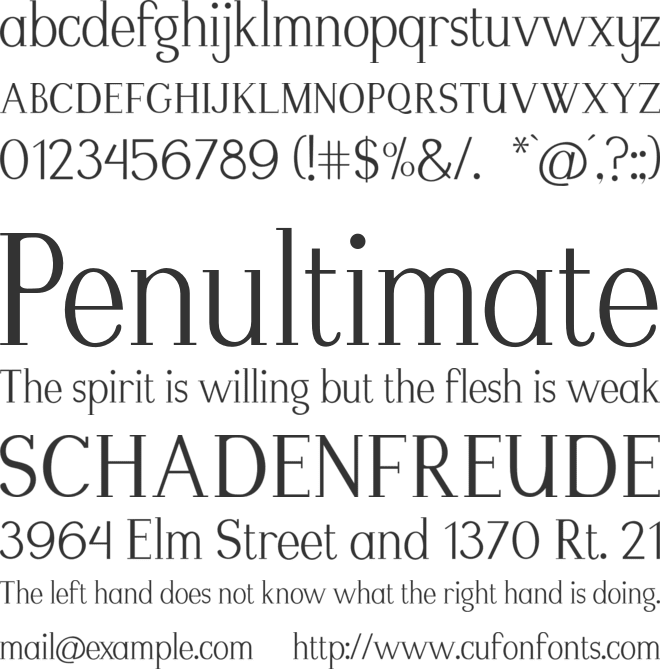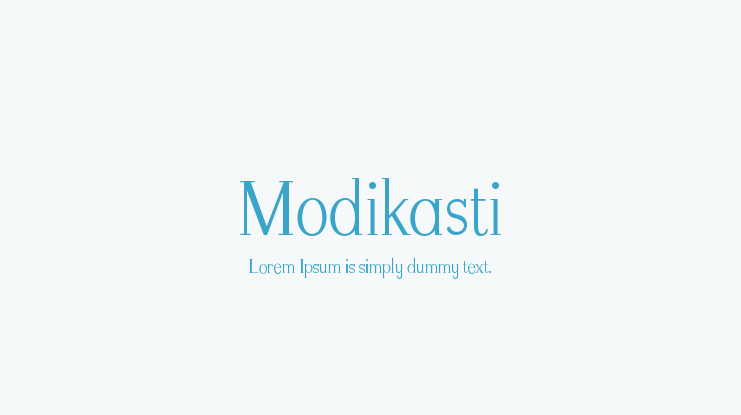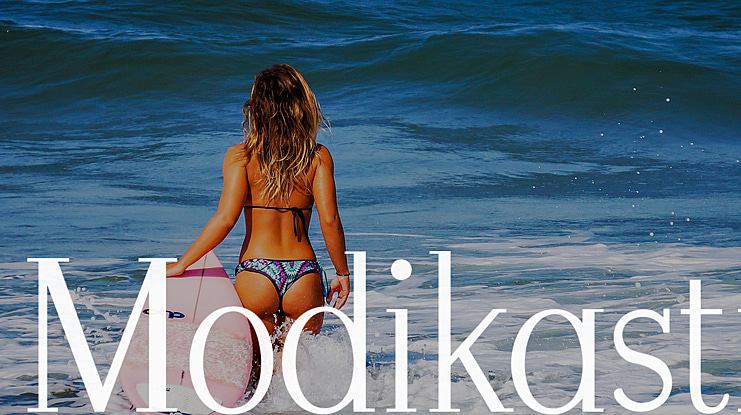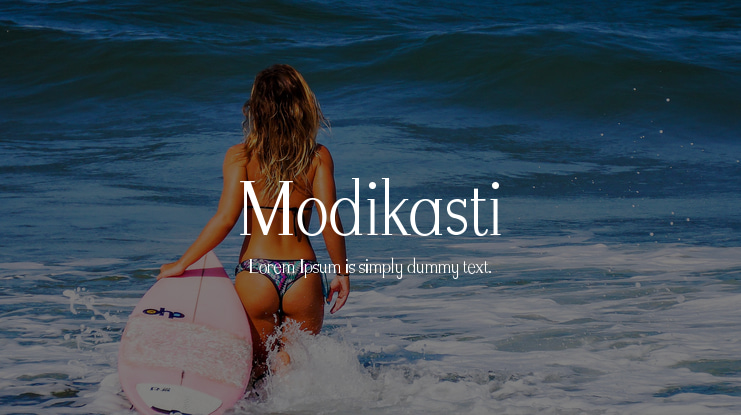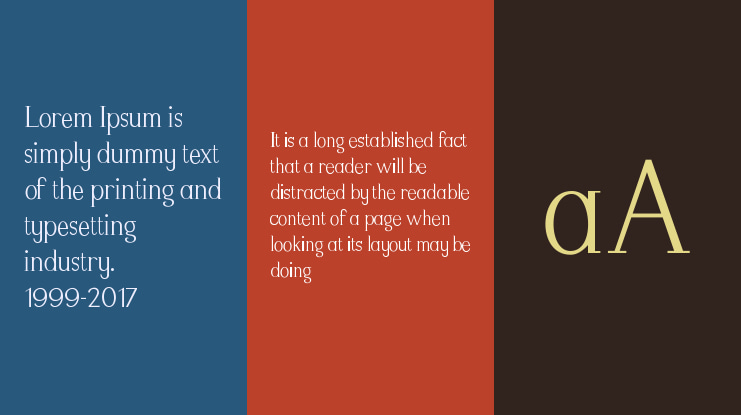
Modikasti Font
Mariana Aguirre Cardoso
Es un tipografía serif, inspirada en la moda. es moderna y divertida. Le puede dar ese toque diferente cualquier documento.